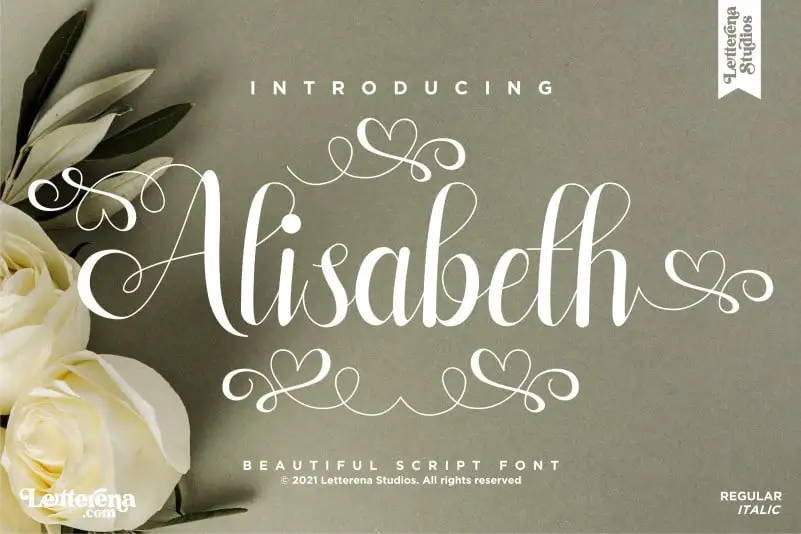
Alisabeth Script Font – Fonte Grátis
Alisabeth Script Font
A fonte ‘Alisabeth Script Font’ é uma bela escolha para qualquer projeto que deseje adicionar um toque de elegância à sua criação. Lançada pela Letterenastudios, esta font é uma delicada chamada escrita, perfeita tanto para projetos como logos e marcas, designs de móveis de casa, embalagens de produtos, chávenas, mensagens e cartazes, sacolas de shopping, camisetas, capas de livros, etiquetas, fotografia, marca d’água ou eventos especiais. Com sua elegância romântica, a ‘Alisabeth Script Font’ combina perfeitamente com uma variedade de projetos que precisam da sofisticação e do encanto de um bom gosto em letras cursivas. Seja para ilustrar sua marca no mundo digital ou para dar vida ao seu projeto gráfico de maneira sofisticada, esta font traz o toque final perfeito.